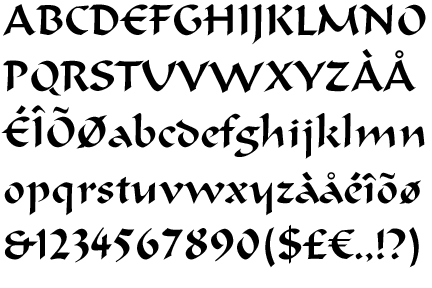
Kennt jemand diese Schriftart?
Auf die Schnelle:
Was da das "Original" ist weiß ich nicht.
da fällt der Groschen ... Das Original sollte folgende Schrift sein:
Ondine
Originally designed by Adrian Frutiger for Deberny & Peignot in 1954.
Designer: Adrian Frutiger
Year: 1954, 1995
Von der Ondine gibt es viele Nachbauten. Eine der am weitesten verbreitete Version könnte die Version von Bitstream sein. Äh? Wie heißt die denn noch?
Die Formal Script 421 habe ich noch in der alten BT-Sammlung vom Corel-Draw. Die dritte Zeile sagt mir, dass es auch eine Version von Softmaker gibt. Habe ich da noch was rumliegen?